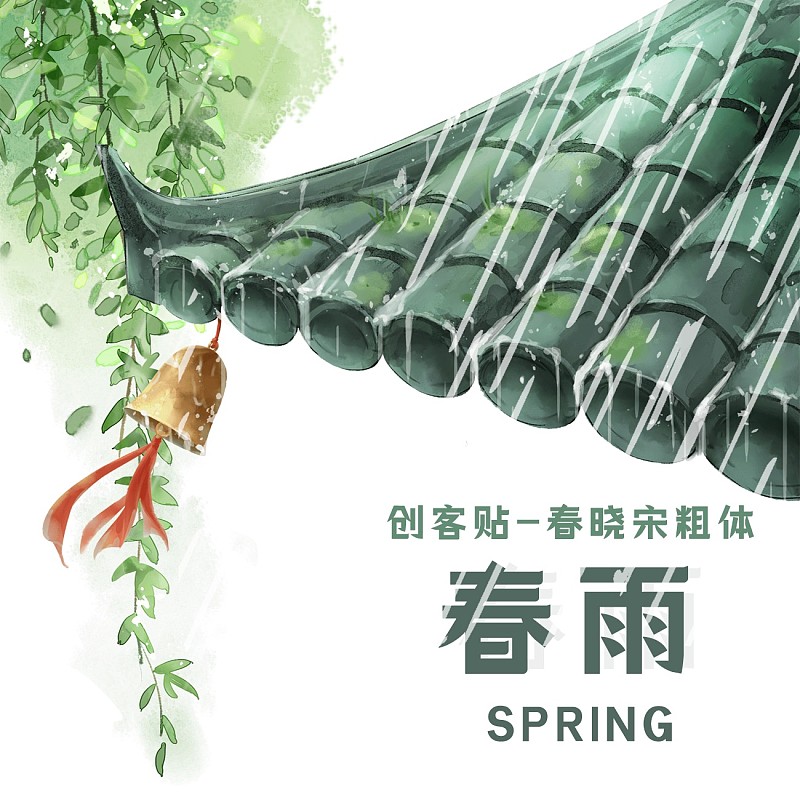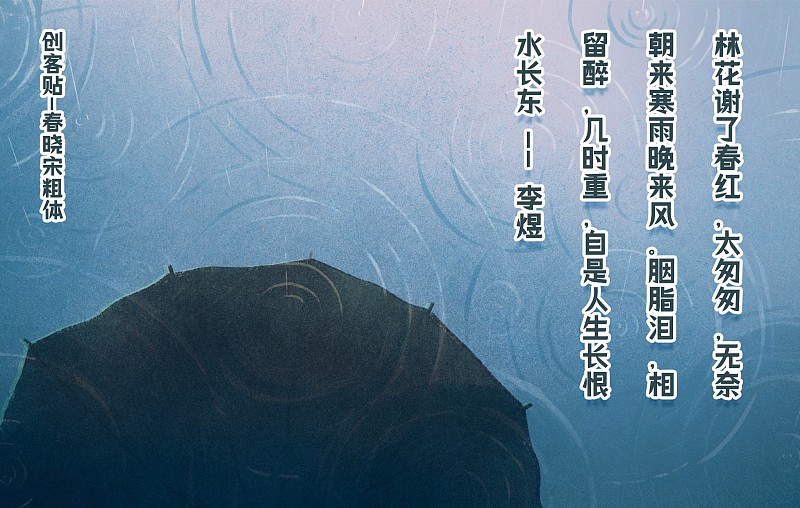
創(chuàng)客貼春曉宋
創(chuàng)客貼春曉宋是一款將黑體宋體主要特征結(jié)合而來的字體,秉承簡潔、時(shí)尚的設(shè)計(jì)手法,是一款廣受用戶好評(píng)的國風(fēng)標(biāo)題字體。
字體類型:宋體, 美術(shù)體, 襯線體
字體風(fēng)格:美術(shù)字體, 廣告字體, 裝飾體
字體用途:廣告, 游戲, 影視, 動(dòng)漫, 電子產(chǎn)品終端, 標(biāo)題